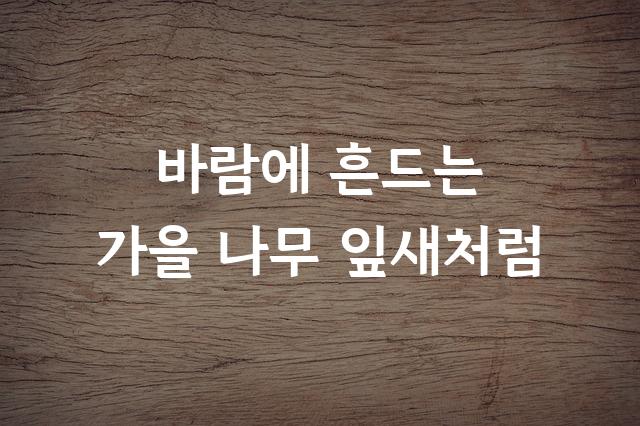
충북대70주년체
충북대70주년체는 둥근 고딕과 장식적인 디자인 요소가 조화롭게 어우러진 폰트입니다. 현대적인 감각과 전통적인 무드가 공존하여 다양한 매체에서 효과적으로 사용될 수 있습니다.
이 폰트의 인사이트!
따뜻하고 친근하며, 동시에 현대적이고 전문적인 느낌을 제공합니다.
충북대70주년체은(는) 기본 고딕, 둥근 스타일, 장식 스타일, 감성적인, 부드러움, 복실복실, 별모양/패턴 계열의 생김새를 가지고 있으며
웹/앱 디자인, 프레젠테이션, 보고서/문서 등에서 자주 활용되며, 효과적인 메시지 전달에 적합합니다.
이 폰트는 교육, 공공/정부, 금융/비즈니스 분야에 잘 어울리며,
신뢰감, 명확한, 전문적인 느낌을 담고 있는 것이 특징입니다.
이 폰트와 유사한 폰트로는 나눔고딕, 맑은고딕, 서울한강체 등이 있어요. 함께 비교해 보시면 좋습니다!